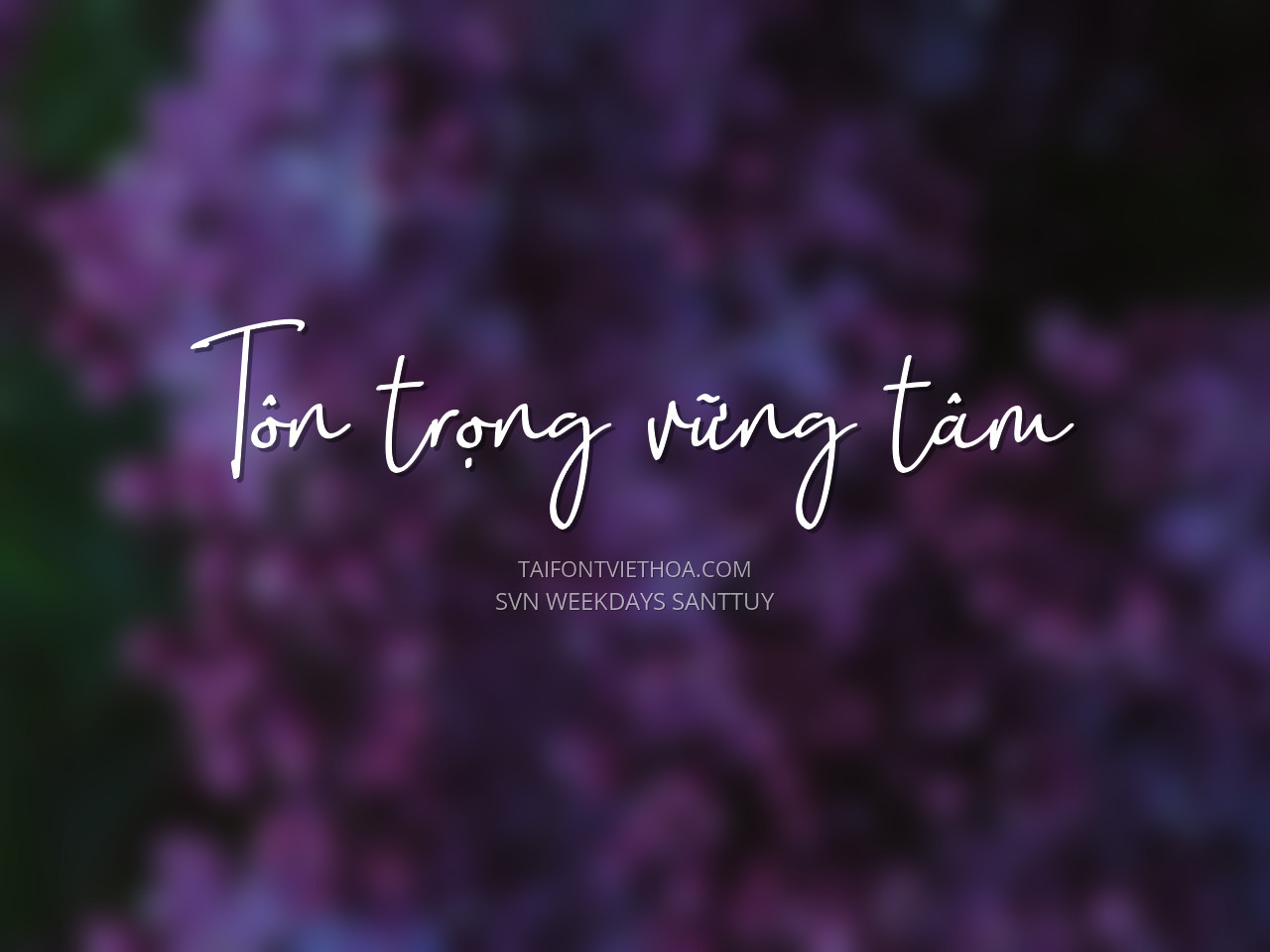
Font việt hóa SVN Weekdays Santtuy
Tác giả Font: Alde Saputro
Giới thiệu về Weekdays Santtuy – chữ viết tay đầy cảm hứng
Weekdays Santtuy (tên gốc: “Weekdays Santtuy Regular”) là phông chữ script viết tay được thiết kế bởi Alde Saputro– nhà sáng lập Aldedesign (Indonesia) và phát hành lần đầu vào năm 2019. Bộ font gốc chỉ gồm một style nhưng được chăm chút bằng công cụ FontCreator 11.5, nhờ vậy giữ được các đường bút uyển chuyển, nhịp điệu mượt mà giữa nét thanh – đậm. Nhờ dựa trên chuẩn Unicode, bản gốc đã hỗ trợ tới 38 ngôn ngữ châu Âu – Mỹ.
Phiên bản SVN Weekdays Santtuybạn đang xem đã được Styleno.1 FontsViệt hóa cẩn thận, bổ sung đầy đủ dấu tiếng Việt, ký tự Latin mở rộng và kerning tối ưu cho văn bản dài. Toàn bộ glyph mới được căn chỉnh lại để giữ nguyên cảm giác viết tay tự nhiên nhưng vẫn đọc tốt ở kích thước nhỏ.
Đặc điểm thiết kế, ứng dụng và ngành nghề phù hợp
Weekdays Santtuy thuộc nhóm script viết tay kết hợp nét bút lượn sóngvà độ nghiêng nhẹ 11°, tạo ấn tượng thân thiện, trẻ trung. Tương phản nét ở mức vừa phải giúp font không bị “quá tay”, duy trì khả năng đọc tối ưu từ 14 pt trở lên. Bộ glyph gồm đầy đủ ligaturesđôi như tt, ll, thgiúp chữ liền nét và cân đối; ngoài ra còn có bộ alternatescho chữ cái đầu – cuối từ, cho phép designer tạo nhịp điệu thị giác linh hoạt.
Ứng dụng điển hình
– Logo & Branding: Nét viết tay mềm mại nhưng rõ ràng, lý tưởng cho logo quán café, tiệm bánh “homemade”, kênh YouTube lifestyle.
– Ấn phẩm sự kiện: Poster Lễ Tình Nhân, tiệc sinh nhật, lễ hội Giáng Sinh cần bầu không khí ấm áp, gần gũi.
– Thiệp & bao bì: Thiệp cưới, danh thiếp spa, nhãn mác mỹ phẩm thủ công…
Ngành nghề khuyên dùng
Ẩm thực – F&B, Spa & Beauty, Wedding Planner, Handmade Craft, Agency quảng cáo kỹ thuật số, shop thời trang nữ boho… đều phù hợp. Khi kết hợp với font sans-serif trung tính, Weekdays Santtuy giúp tiêu đề nổi bật mà không làm nhiễu thông tin chính.